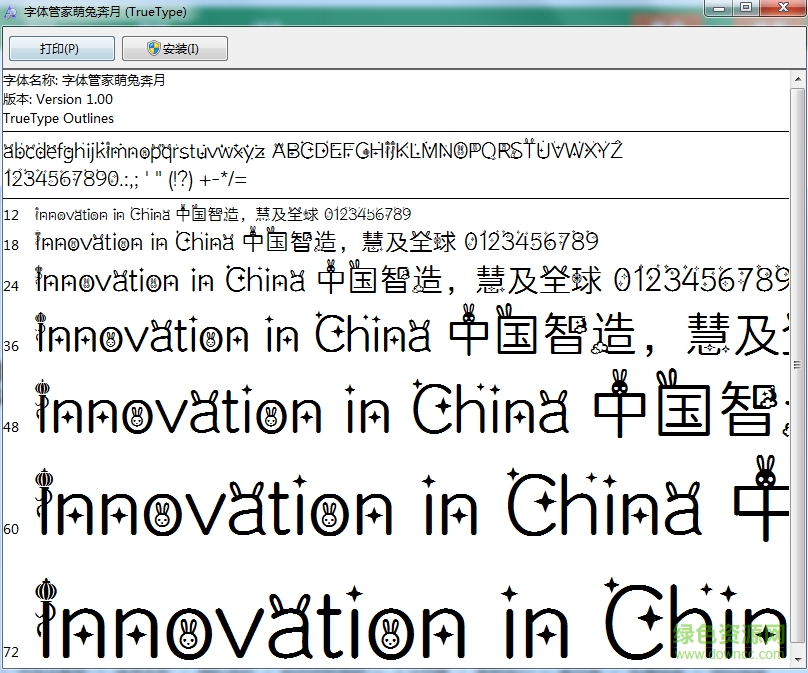
萌兔奔月是字體管家上一款非?;顫娍蓯鄣?a href="http://m.lz0519.com/k/katongziti/" target="_blank">卡通字體,各種萌兔圖案點綴,讓你感受字里行間的同趣和童真,喜歡的朋友快來綠色資源網(wǎng)下載吧!
萌兔奔月字體管家的一款常規(guī)字體,共有22601個字符,基本覆蓋所有文字和符號。